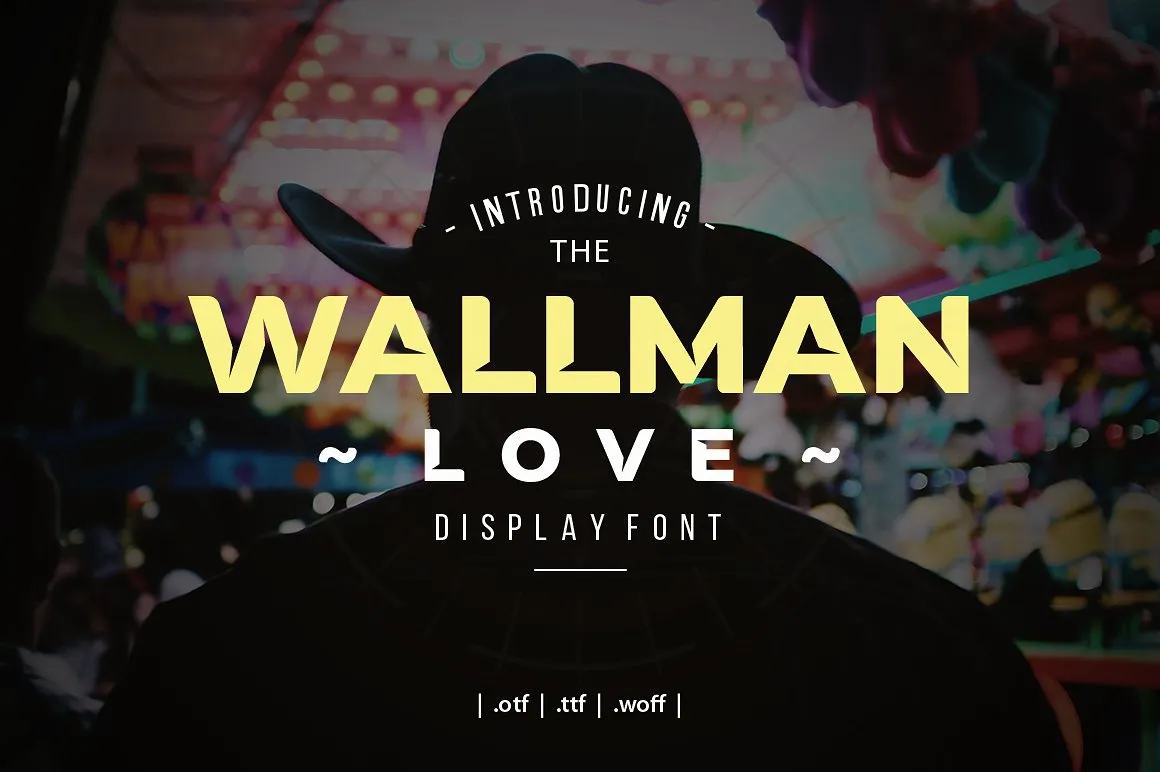
Wallman Love Display Font – Fonte Grátis
Wallman Love Display Font
Aqui está uma descrição em português do Brasil para a página de download da fonte ‘Wallman Love Display Font’, mantendo as restrições e orientações fornecidas: Esta fonte, chamada Wallman Love Display, é perfeita para quem busca um olhar vintage ou linhas suaves de desenho à mão. É uma excelente escolha para projetos que exigem um estilo clássico, como logotipos ou capas de álbuns musicais. Se você está procurando por algo atraente e criativo para aplicar em roupas ou artigos de design, este é o tipo de fonte perfeito. A Wallman Love Display foi projetada com uma versão em minúsculas e maiúsculas, incluindo dígitos e caracteres internacionais. Ela se destaca como um recurso útil para criações de mídia social, material gráfico ou qualquer outra aplicação que requer um design atraente e único. Seja você um designer de arte digital, uma marca buscando uma identidade visual única ou apenas alguém com o hábito de criar projetos pessoais únicos, essa fonte oferece a oportunidade de adicionar um toque personalizado ao seu trabalho. Com sua elegância e versatilidade, a Wallman Love Display é uma escolha inteligente para qualquer projeto que deseje dar uma camada extra de beleza e personalização à sua arte digital ou design gráfico.